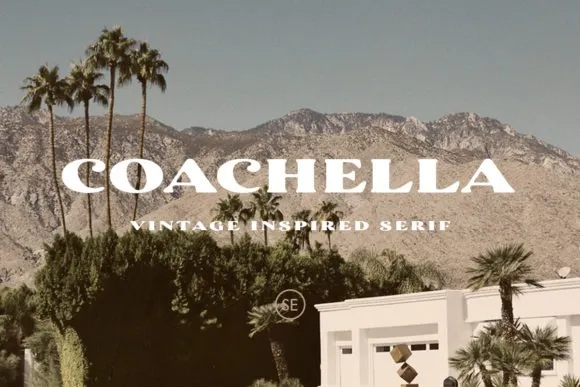
Descubra a exquisitez do Coachella Font, uma elegante serif retro com toques artísticos perfeitos para qualquer projeto. Seja ele uma panfletagem sofisticada, um anúncio de evento musical ou até mesmo o design de sua marca ideal, esta fonte traz nuances que tornam a criação ainda mais autêntica e cuidadosa. Atraente por sua tipografia serifada em maiúsculas com toques artísticos é projetada para qualquer projeto gráfico, mas também oferece detalhes suaves que dão um toque de originalidade à sua obra. Esta fonte é especialmente versátil e suporta múltiplas línguas, tornando-a a escolha perfeita para uma variedade impressionante de tarefas design. Com certeza irá deixar seu design mais elaborado e cuidadosamente detalhado.